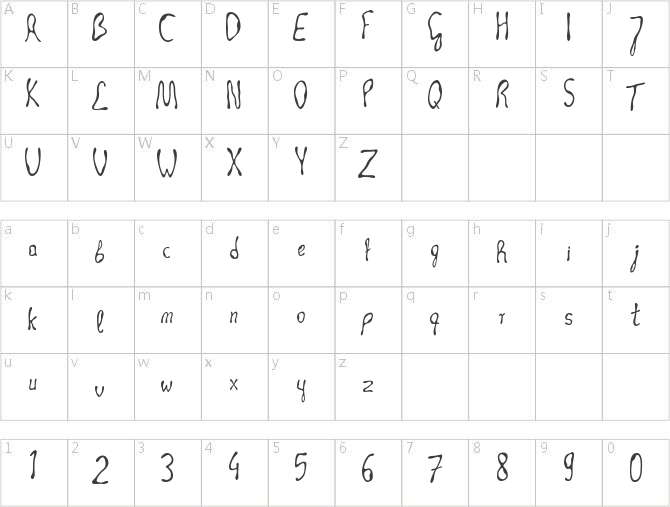
Occult-TechniqueRegular
Occult-TechniqueRegular介紹
Occult-TechniqueRegular字體字庫是一款讓人賞心悅目、百看不厭的英文字體,適合各類廣告和產品包裝設計應用,字體大小0.02MB,格式為ttf字體,上傳用戶是凡塵之間,作者/版權方為未知